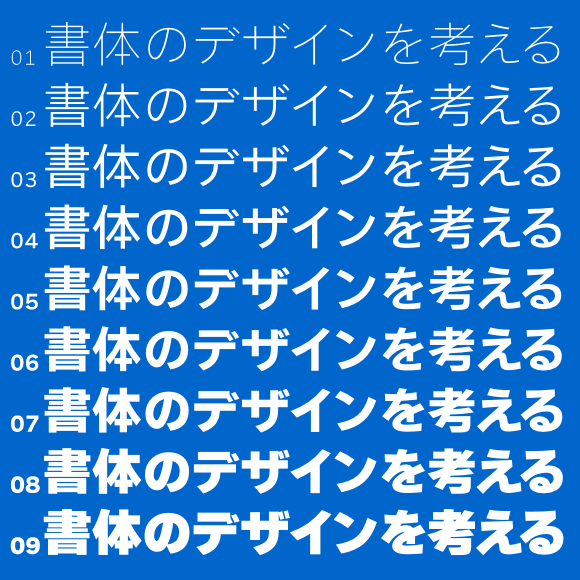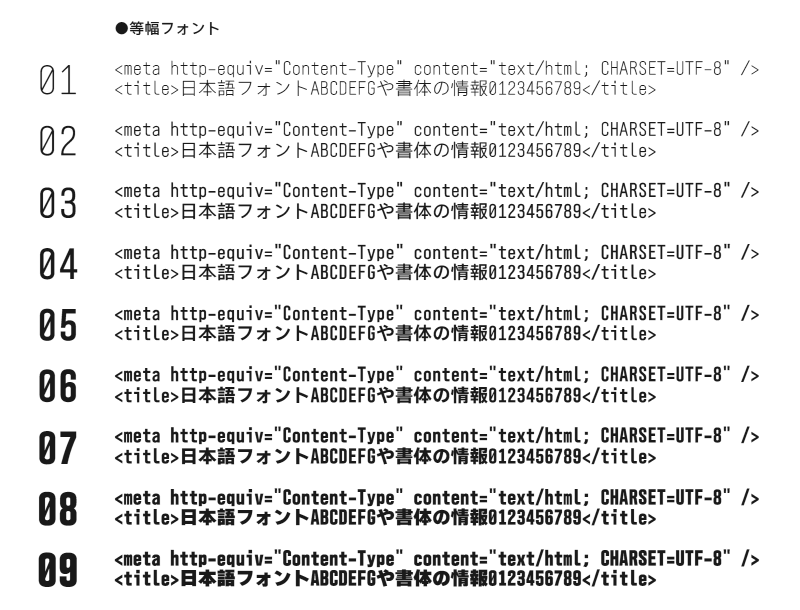
デザイン 大きめで読みやすく、クセのないシンプルなデザインです。
太さが9種類あるので、使用環境や目的に合った最適なフォントが選べます。
等幅バージョンは、英大文字のアイ「I」と英小文字のエル「l」数字のいち「1」や、英大文字のオー「O」と数字のゼロ「0」が、はっきり区別がされているので、URL表記やプログラム編集などにぴったりです。
NEC特殊文字とIBM拡張文字も使えるようになりました。
連想されるイメージ
寄せられたコメントから抜粋
美しい・柔らかい・読みやすい・キレイで凛としている・シンプル・やさしい・温かい・誠意を感じる・癖がない・標準的・バランスが良い・気持ち良い・ナチュラル・明るい・すっきりしている・落ち着きを感じる・安定している